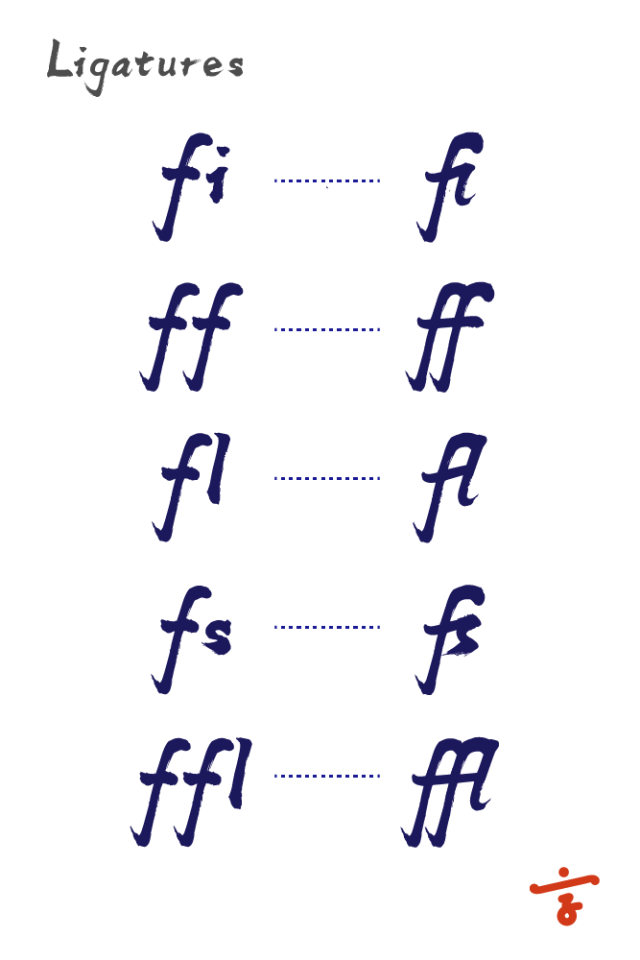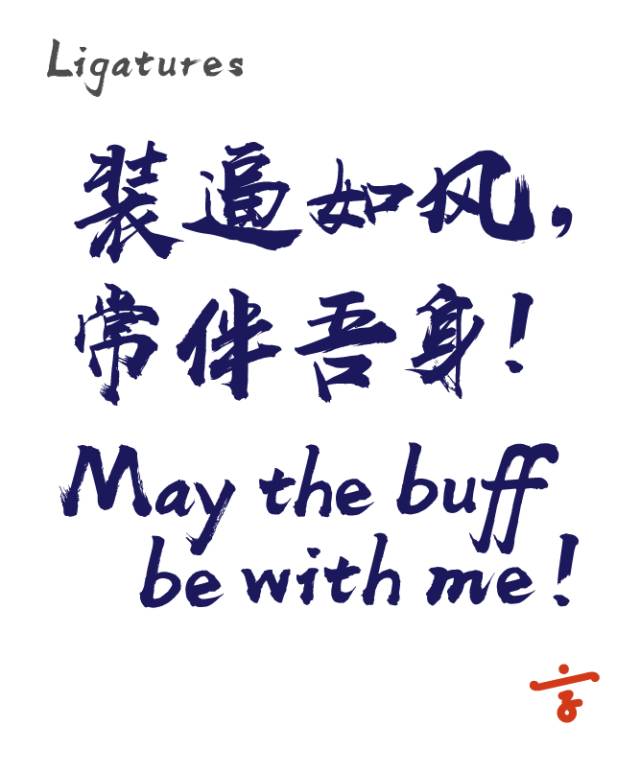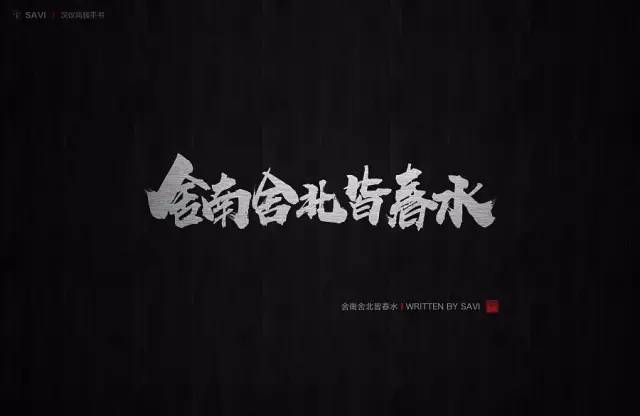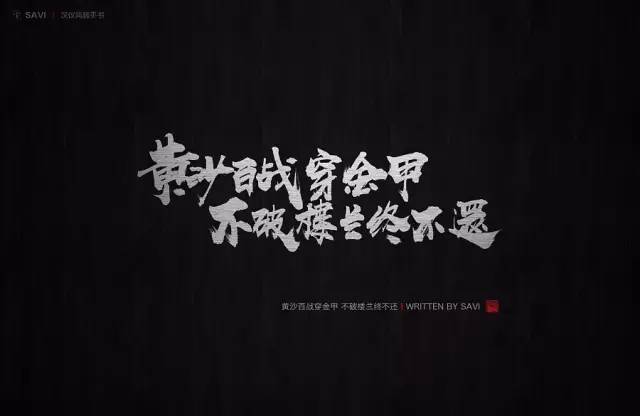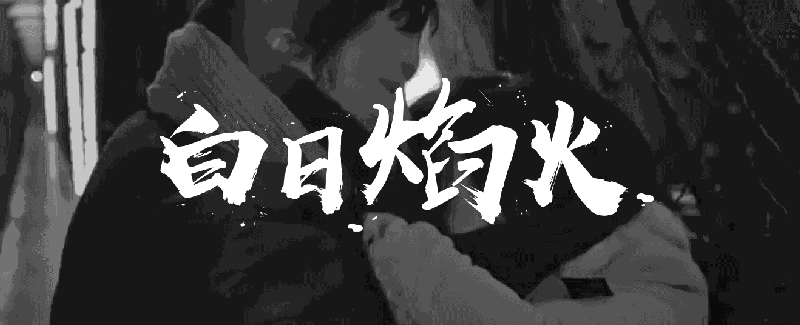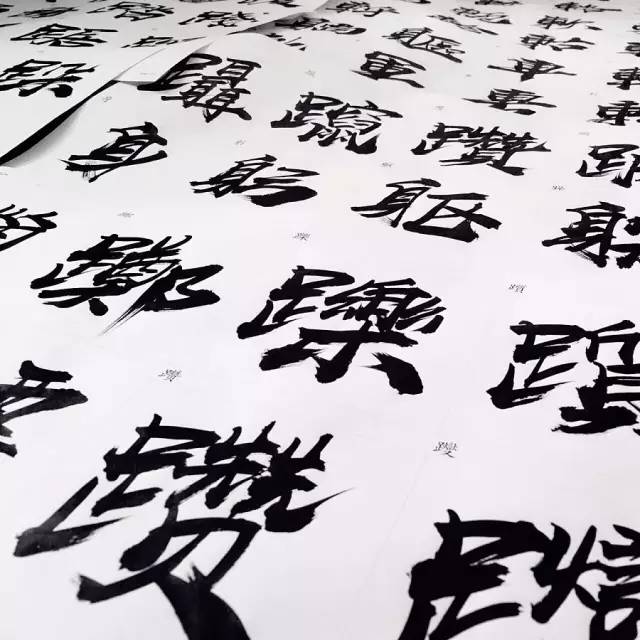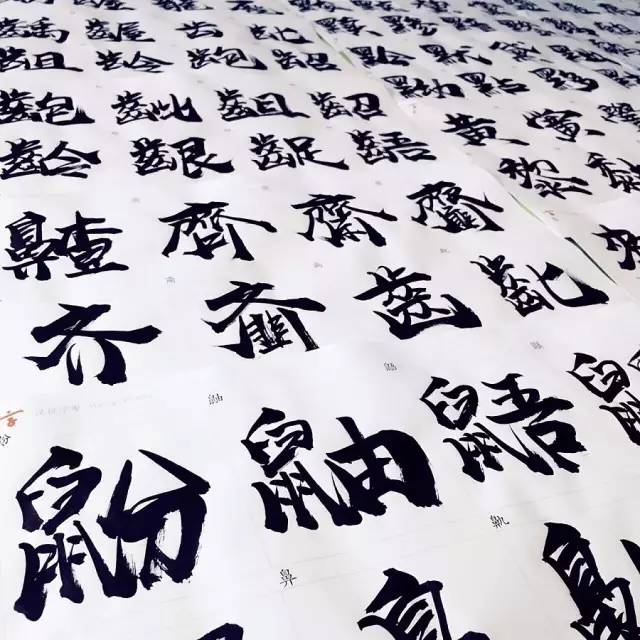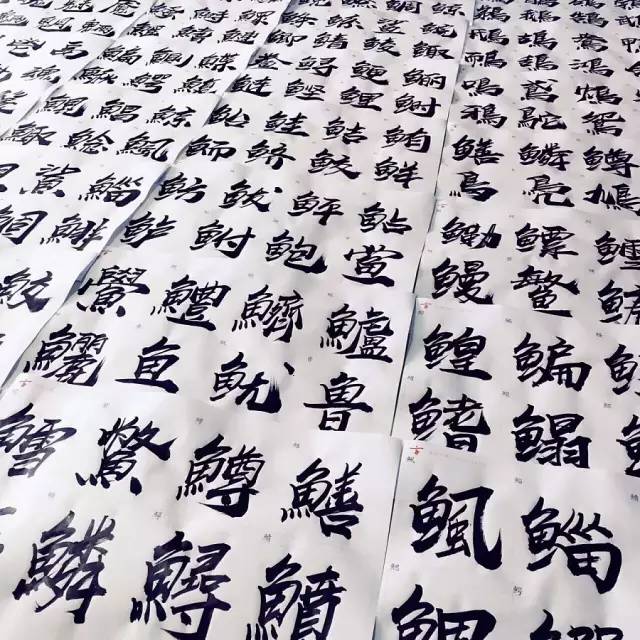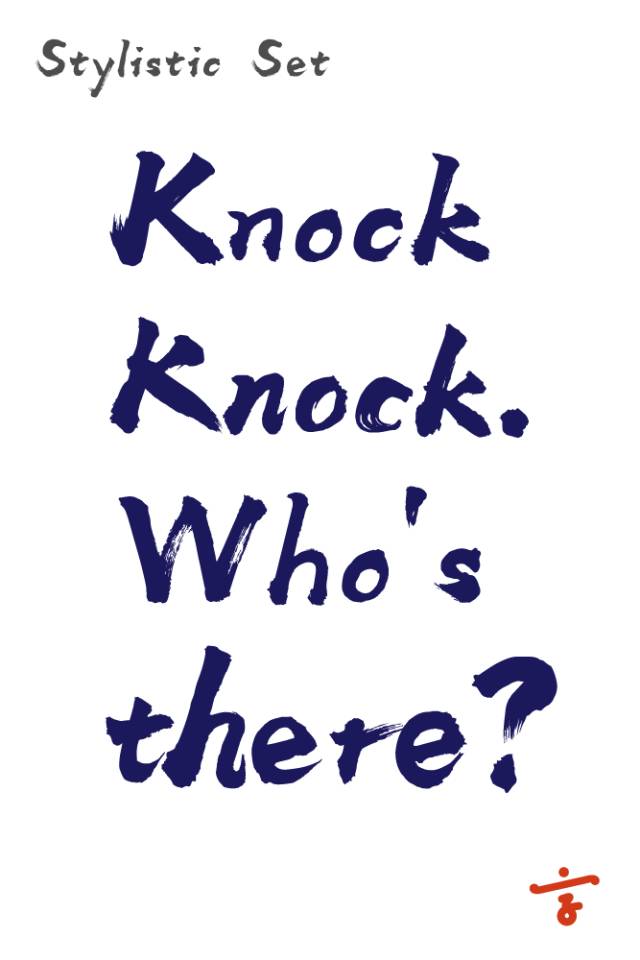
汉仪尚巍手书字体介绍,汉仪尚巍手书字体案例、适用场景
五岁开始练字,
期间兜兜转转做过很多事,
最后又兜兜转转回到了手写行业,
开始懂得坚持,
开始想要做极致。
很多人问我为什么这么多年还在不停写字?
其实坚持手写至今是因为:
我觉得笔呈现在纸张上面的文字远比屏幕上的有份量。
——书写人 尚巍
字库+英文+日文+标点10000余字。
手写文件耗时21天。
平均每天书写时间10+小时。
报废4支毛笔。
用尽3瓶500g墨汁。
后期一次修改800余字。
后期二次修改100余字。
后期文件处理耗时70天。
字库总耗时91天。
字库数据量16.2M。
字库特点
强劲张力
字体笔画粗壮,尾部的甩尾有力且有丰富的笔触细节,大字效果突出且引人注目。
还原度高
最大程度还原作者书写字形,细节表现完整。同时数据量比较大,不管是飞白还是连笔都有着很好的表现,边缘清晰流畅,为使用这款字体设计师在设计表现力中提供最大程度书法感觉的还原。
不一样的拉丁字符
Stylistic Set两套可选的风格样式
Oldstyle 不齐线数字
Ligatures ff / fi / fl / fs等连字效果
应用范围
标题 / 包装 / 电商
体育 / 游戏 / 互联网 / 中国风
产品规格
汉仪尚巍手书 | HYShangWeiShouShuW
9169汉字 | 中文简繁
创作团队
字库书写人 | 尚巍 SAVI
一个行走于机打时代的手写人
跨界设计师 美学创意人 书法创作人
他,90后,
却花了20年的时间不断诠释他对书法的情怀。
他,在这个浮躁的年代,
坚持着自己的手写风格,不骄不躁。
他,被称作是一个带着传统,却敢倒立行走的新生代艺术家。
字体应用展示